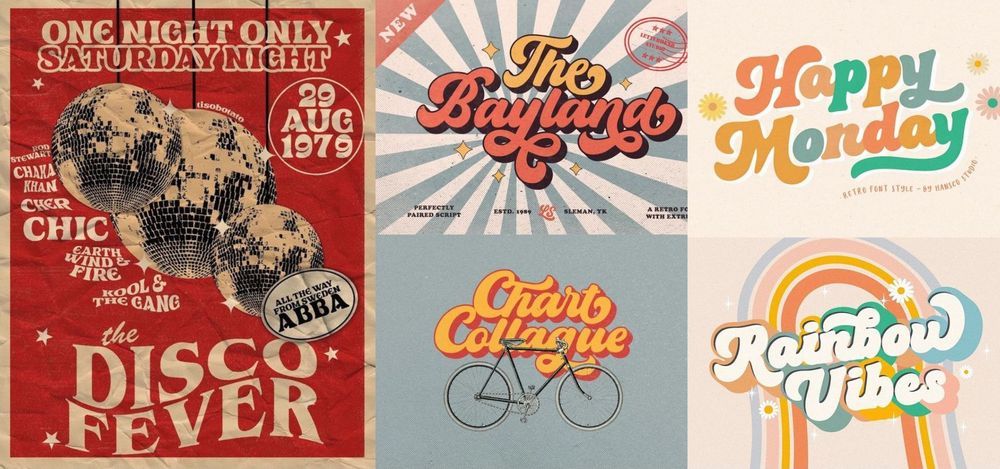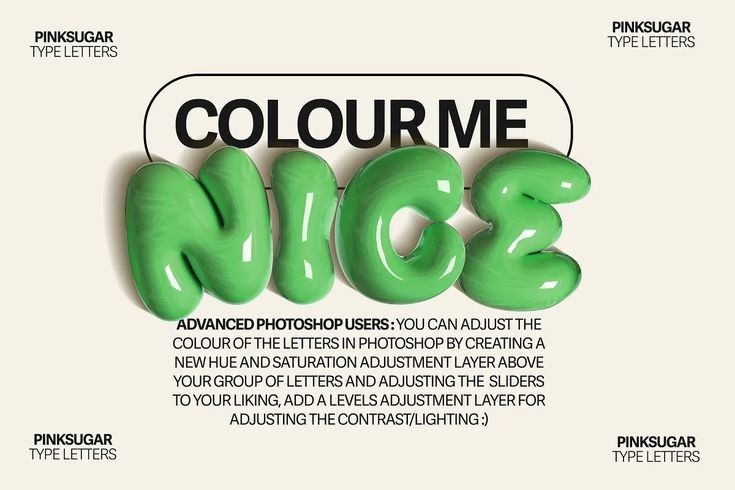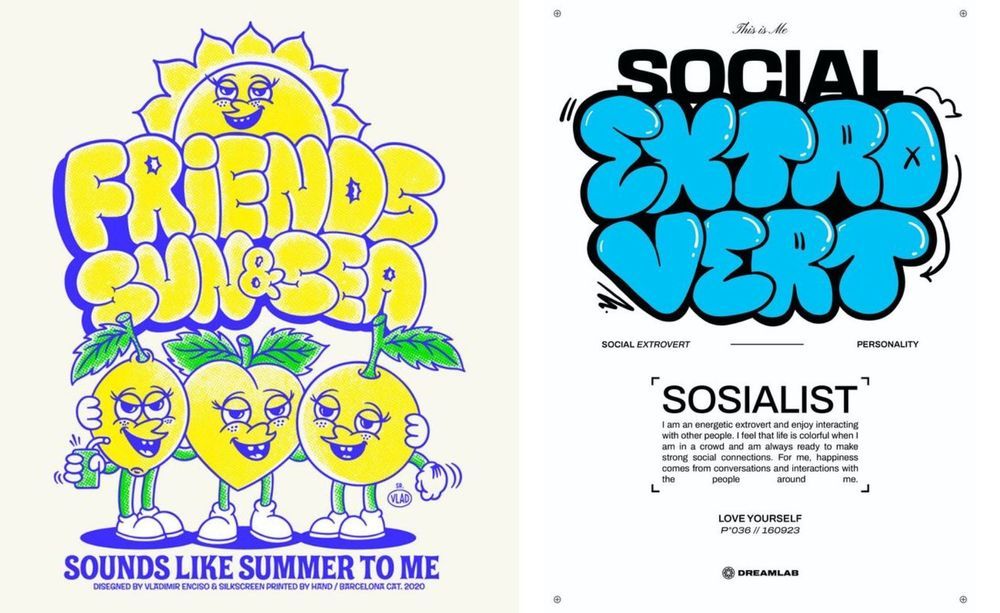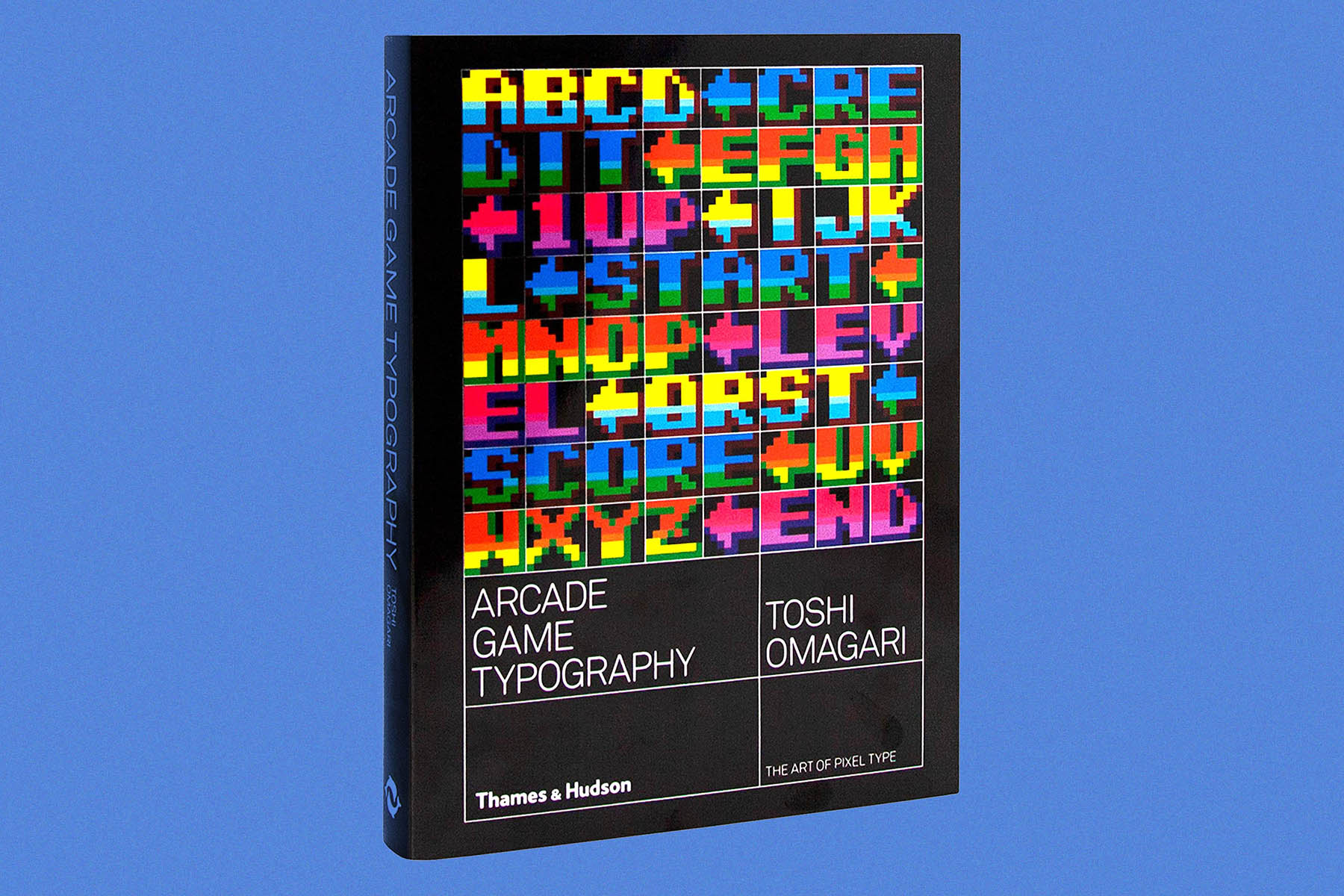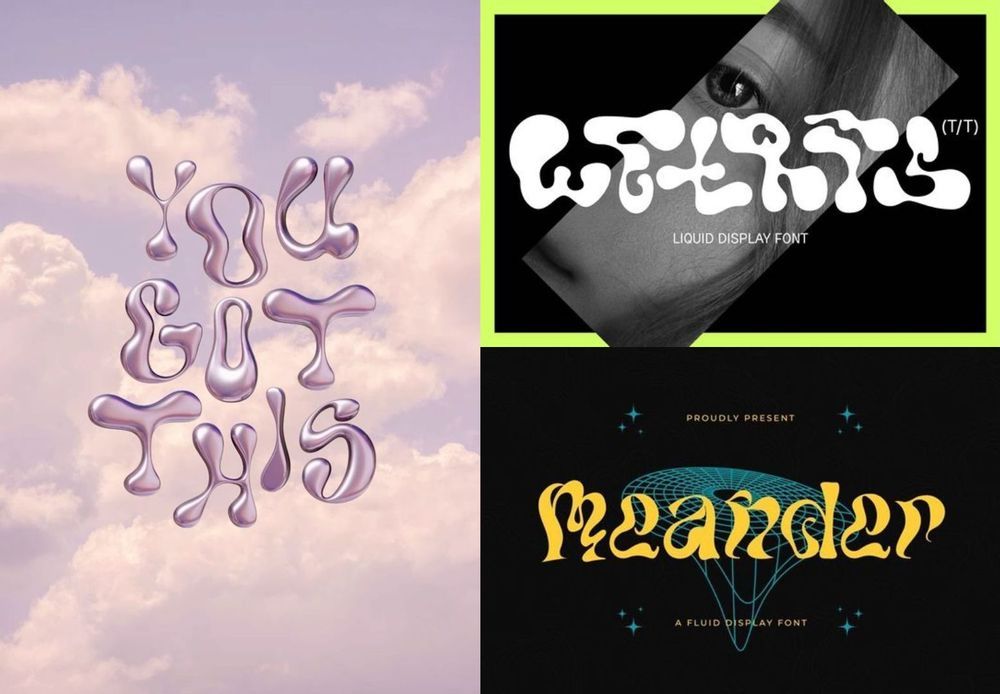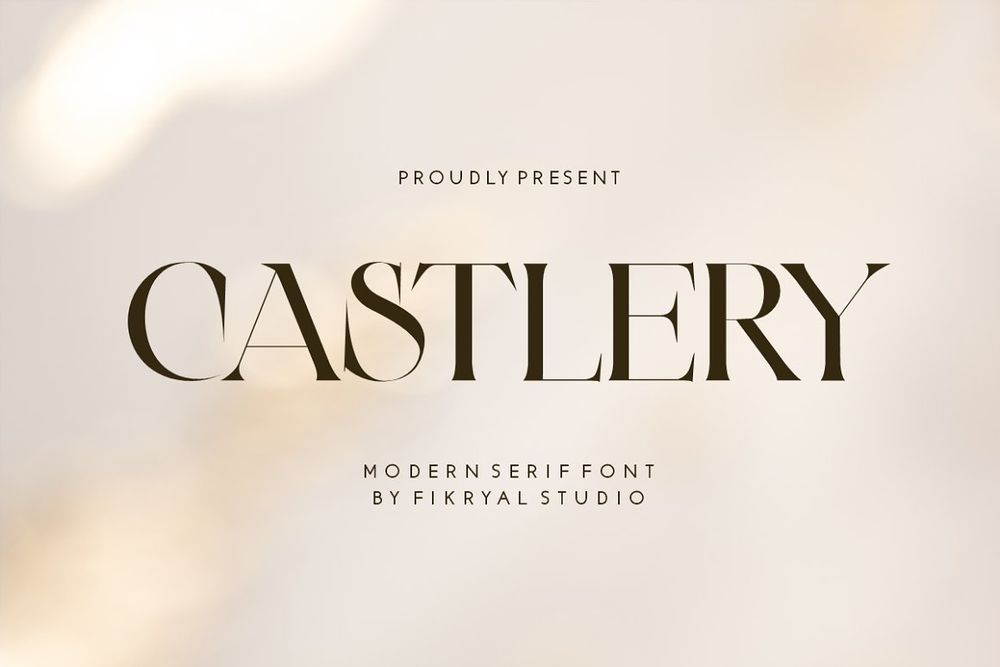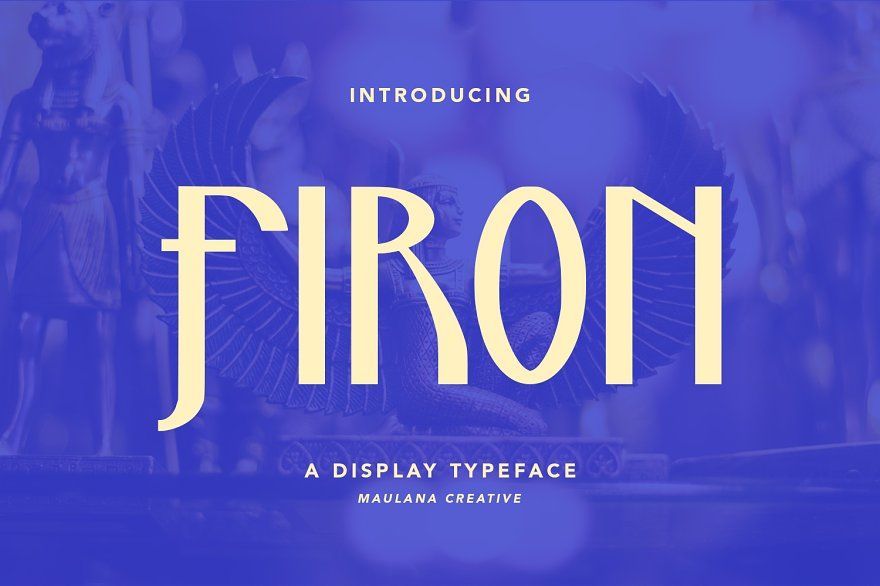
7 xu hướng sử dụng kiểu chữ đậm tính nghệ thuật năm 2024
Là một trong những yếu tố quan trọng nhất trong Typography (nghệ thuật tạo và sắp xếp văn bản), kiểu chữ giúp định hướng hình ảnh thương hiệu và góp phần truyền tải thông điệp hiệu quả. Hãy cùng Bee Art tìm hiểu 7 xu hướng sử dụng kiểu chữ đậm tính nghệ thuật năm 2024 nhé!
Xu hướng sử dụng kiểu chữ năm 2024
Trong thế giới kinh doanh đầy cạnh tranh ngày nay, việc tạo ra ấn tượng ban đầu mạnh mẽ và tối ưu hóa trải nghiệm của khách hàng là yếu tố quyết định sự thành công của một doanh nghiệp. Một trong những yếu tố không thể phủ nhận trong quá trình này chính là Typography - nghệ thuật sắp xếp và thiết kế chữ viết trong thiết kế đồ hoạ.
Typography không chỉ là việc chọn một loại chữ đẹp mắt để sử dụng trong các tài liệu, trang web hay logo của doanh nghiệp. Nó là một phần không thể thiếu của việc xây dựng thương hiệu và tạo dấu ấn riêng biệt. Sự chọn lựa kỹ lưỡng về kiểu chữ có thể phản ánh đúng phong cách và giá trị của thương hiệu, giúp tạo ra một ấn tượng mạnh mẽ và nhận diện dễ dàng trong tâm trí của khách hàng.
Typography cũng là một phần quan trọng trong việc truyền đạt thông điệp của doanh nghiệp. Mỗi loại kiểu chữ mang trong mình một cảm xúc và tinh thần riêng, và việc chọn lựa đúng kiểu chữ có thể làm tăng tính thuyết phục của thông điệp, từ việc quảng cáo sản phẩm đến viết bài blog.
Việc thích nghi và áp dụng các xu hướng mới trong Typography giúp doanh nghiệp tạo ra sự hiện đại và thu hút, đồng thời phản ánh sự linh hoạt và sáng tạo của thương hiệu. Điều này có thể giúp doanh nghiệp thu hút được đối tượng khách hàng mục tiêu, đặc biệt là trong một thị trường luôn biến đổi như ngày nay.
Là một trong những yếu tố quan trọng nhất trong Typography (nghệ thuật tạo và sắp xếp văn bản), kiểu chữ giúp định hướng hình ảnh thương hiệu và góp phần truyền tải thông điệp hiệu quả.
Xu hướng sử dụng kiểu chữ năm 2024
Trong năm 2024, các kiểu chữ được nhận định sẽ là sự kết hợp giữa nghệ thuật, đổi mới và xu hướng hoài niệm.
Xu hướng kiểu chữ lấy cảm hứng từ các thập niên cũ
Cùng xu hướng sử dụng Nostalgia Marketing nở rộ trong nhiều năm trở lại đây, kiểu chữ lấy cảm hứng từ xu hướng thiết kế của những thập niên cũ cũng “phủ sóng” trong nhiều dự án.
Xu hướng kiểu chữ lấy cảm hứng từ các thập niên cũ
Kiểu chữ này thường có các hình dạng hình học độc đáo, các đường cong cường điệu, đậm nét và các chi tiết hấp dẫn vui tươi. Điều này gợi nhớ đến các áp phích, bìa album disco và các quảng cáo cổ điển với vẻ ngoài táo bạo và tràn đầy năng lượng.
Việc sử dụng kiểu chữ này hoàn hảo để tạo ra bầu không khí hoài cổ trong các dự án thiết kế khác nhau, từ xây dựng thương hiệu theo chủ đề cổ điển đến các chương trình khuyến mãi, sự kiện. Ngôn ngữ hình ảnh mang tính biểu tượng của một thập kỷ năng động và đầy màu sắc tô điểm thêm sự độc đáo, nét quyến rũ cổ điển và biểu cảm cho các thiết kế.
Xu hướng kiểu chữ 3D
Kiểu chữ 3D là một trong những xu hướng chính được các nhà thiết kế sử dụng trong năm 2024. Họ nắm bắt được chiều sâu và sự hấp dẫn trực quan mà các dạng chữ ba chiều mang lại. Việc sử dụng các chữ cái 3D biến văn bản đơn giản thành trải nghiệm sống động, đáp ứng nhu cầu tương tác và gắn kết của người dùng.
Xu hướng kiểu chữ 3D
Khả năng sáng tạo với chữ 3D dường như được mở rộng vô hạn. Từ nét cổ điển trong các thiết kế hoài cổ, sự vui nhộn khi kết hợp với các kiểu chữ bong bóng hay nét tinh tế, hiện đại trong các dự án về công nghệ,... chữ 3D đều có thể đáp ứng tốt và mang lại hiệu ứng độc đáo và thu hút.
Xu hướng kiểu chữ bong bóng
Đặc trưng bởi các hình dạng tròn trịa, mềm mại gợi nhớ đến bong bóng, những mẫu chữ này mang lại cảm giác thân thiện và dễ tiếp cận. Tính linh hoạt của xu hướng cho phép nó tích hợp với nhiều chủ đề khác nhau, từ giản dị và vui nhộn đến thời thượng và hiện đại. Với tính thẩm mỹ vui tươi, phông chữ bong bóng đang tạo nên làn sóng vào năm 2024.
Xu hướng kiểu chữ pixel
Xu hướng kiểu chữ pixel
Cùng với làn sóng hoài niệm, kiểu chữ pixel gợi lên cảm giác về đồ họa máy tính thời kỳ đầu. Tận dụng sức hấp dẫn của nghệ thuật pixel với các hình vuông hoặc hình chữ nhật, kiểu chữ này đặt để thêm yếu tố đương đại để mang lại cảm giác khác biệt, kết nối quá khứ và hiện tại một cách quyến rũ về mặt thị giác.
Xu hướng kiểu chữ chất lỏng
Đặc trưng bởi những hình khối tự nhiên, uyển chuyển và những đường cong mượt mà, những kiểu chữ này gợi lên cảm giác chuyển động và linh hoạt. Cho dù được sử dụng để xây dựng thương hiệu, thiết kế biên tập hay giao diện web, sự linh hoạt độc đáo của nó đều mang đến sự mới mẻ và hiện đại, hấp dẫn người xem tương tác.